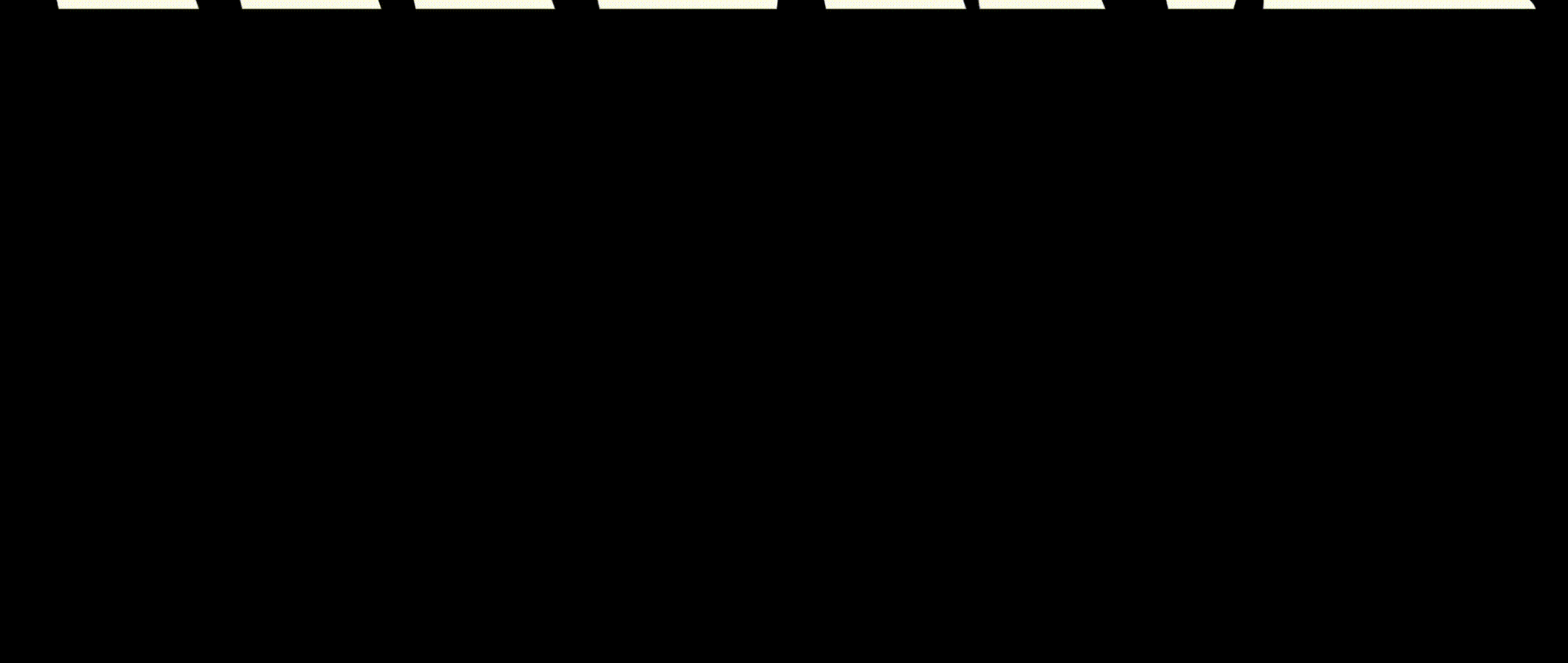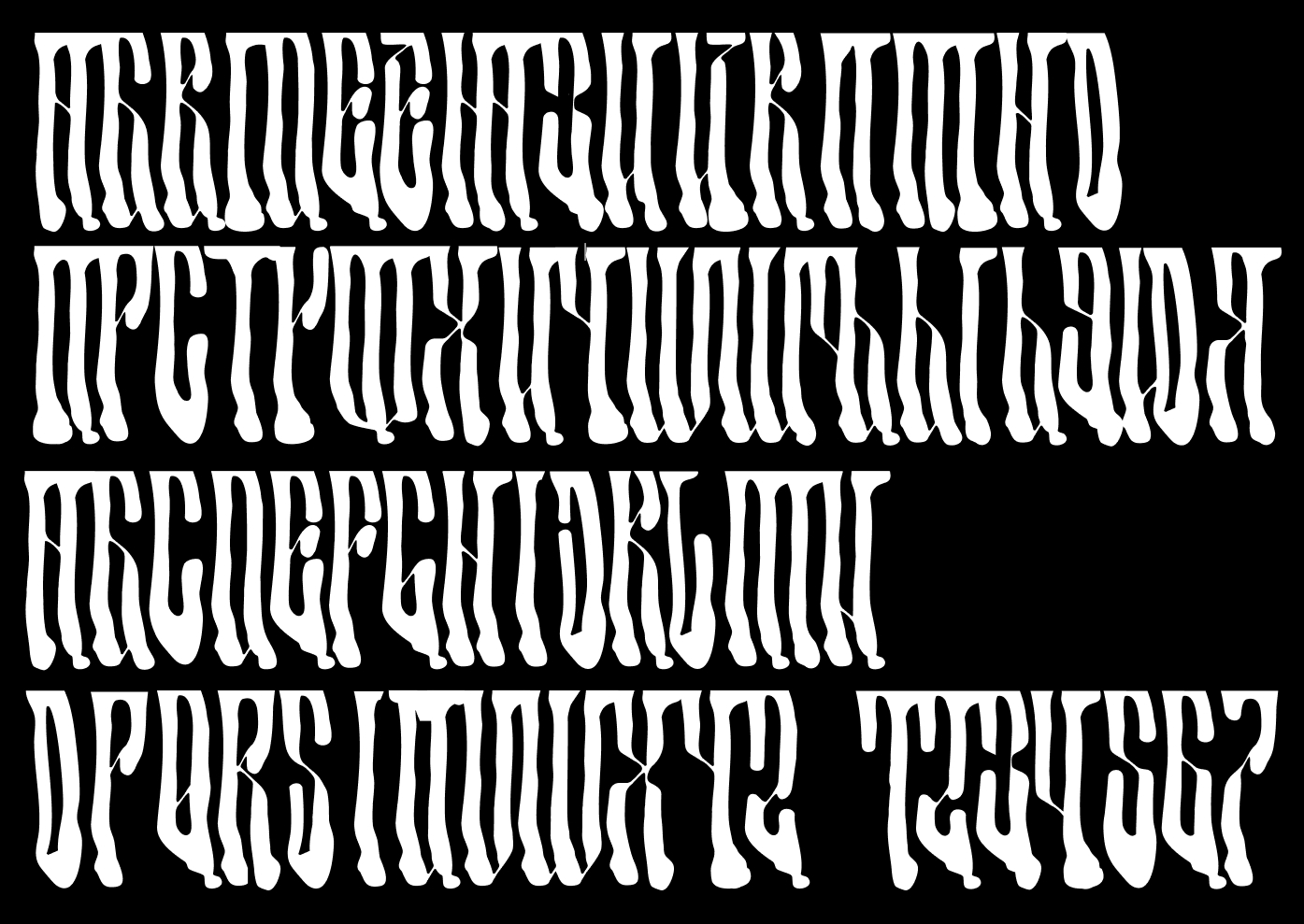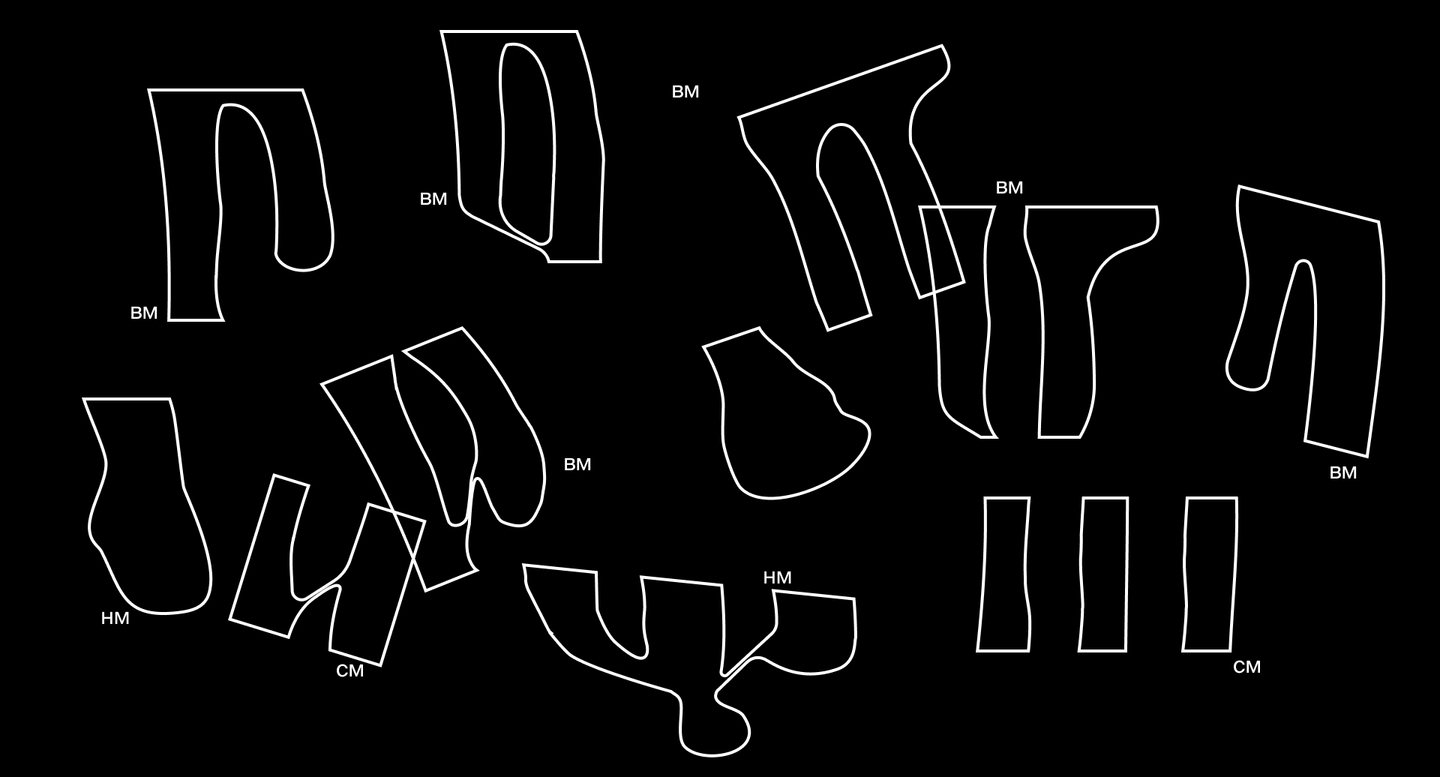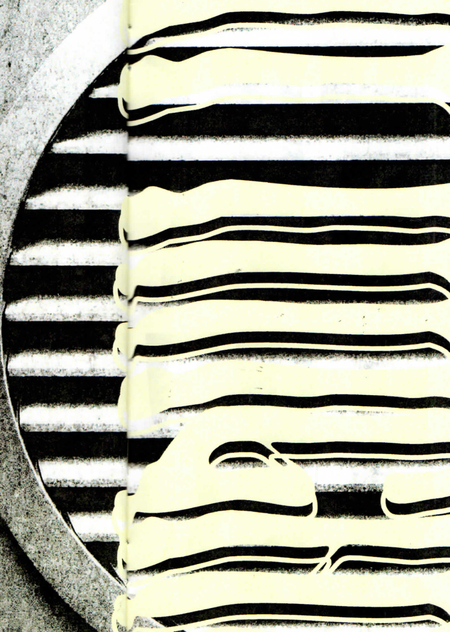
Шрифт создан на основе подтёков неизвестного происхождения, которые стекали из вентиляции возле автобусной остановки у моего дома. В этих случайных следах я увидела формы букв и модульную систему, которая стала основой гарнитуры.